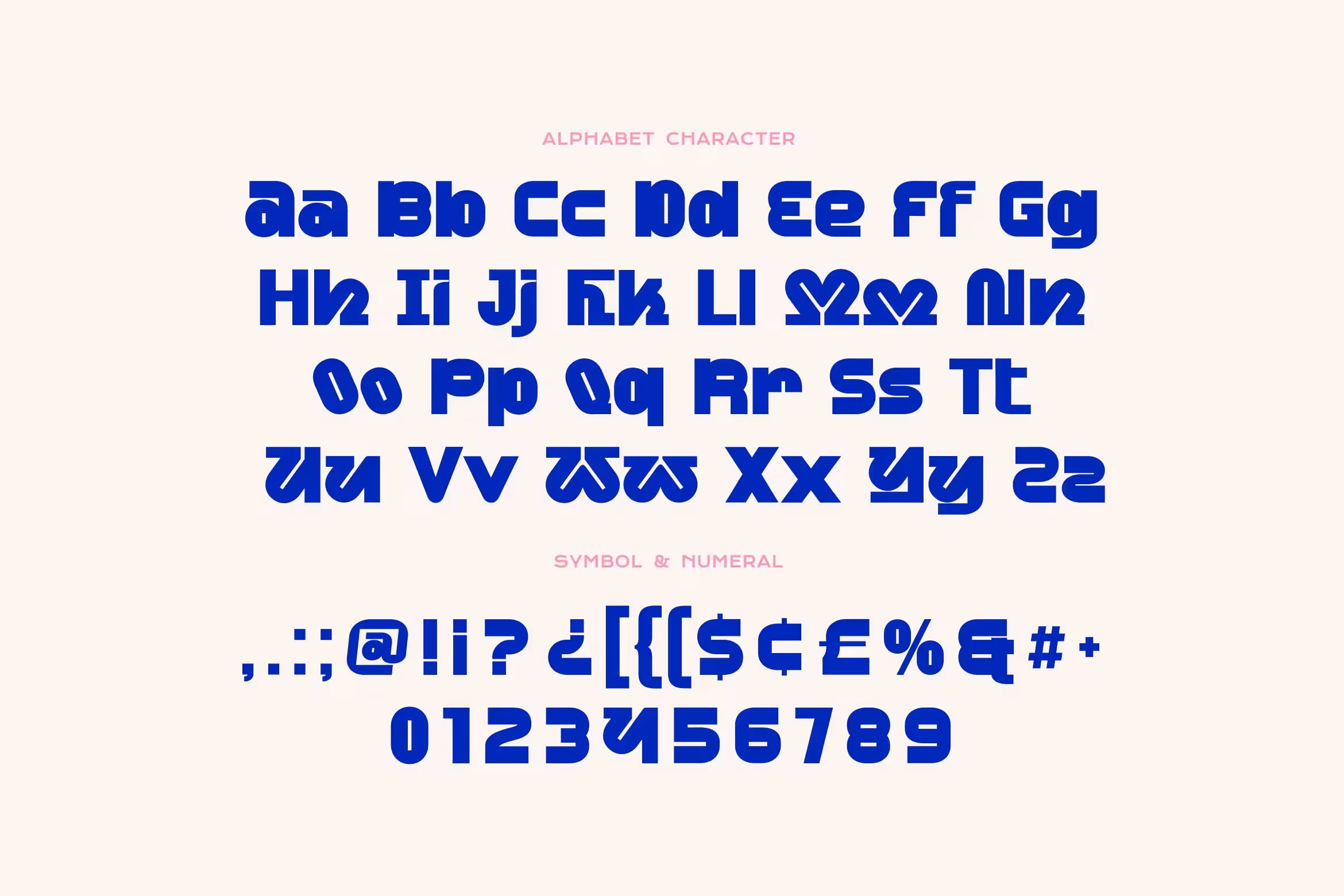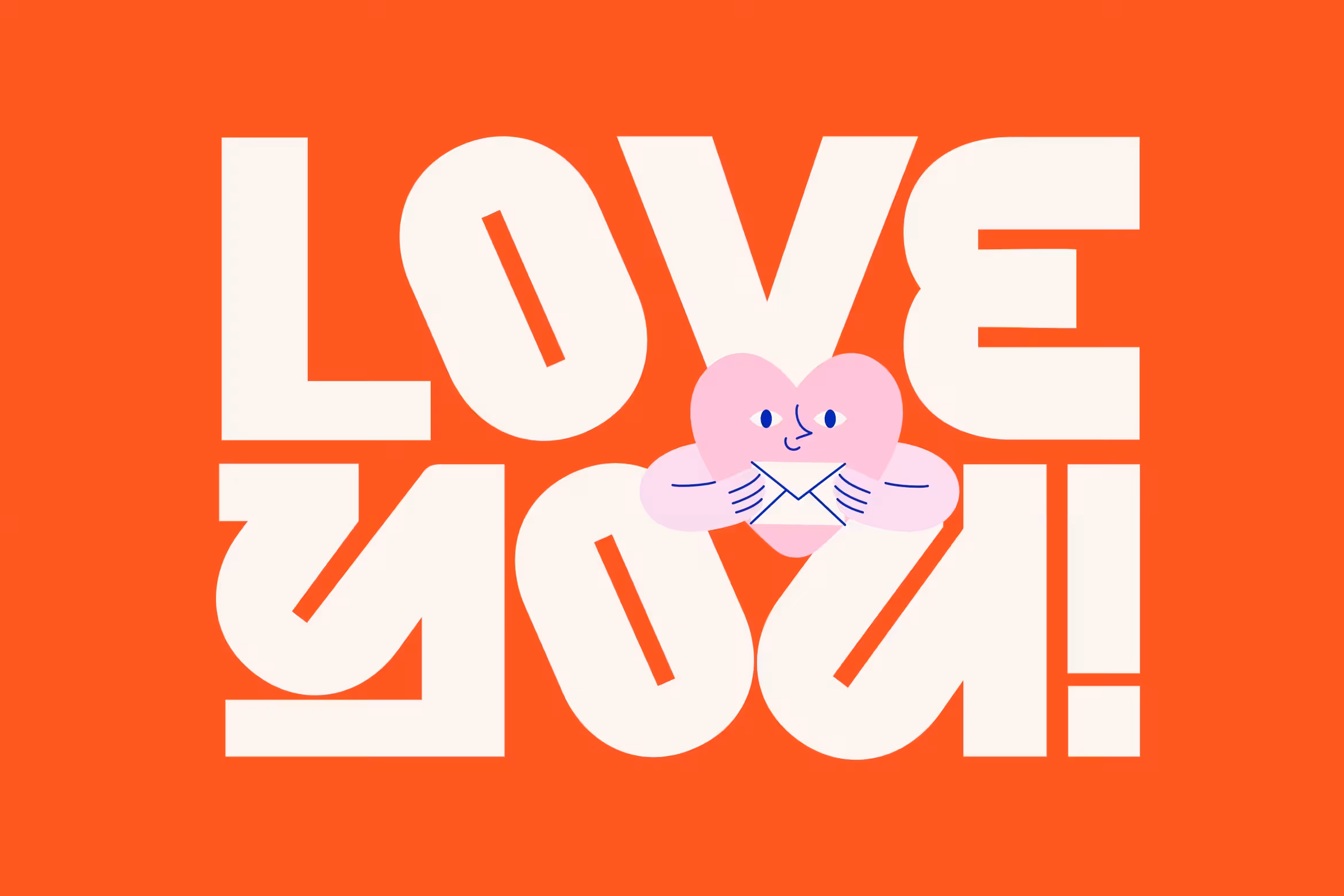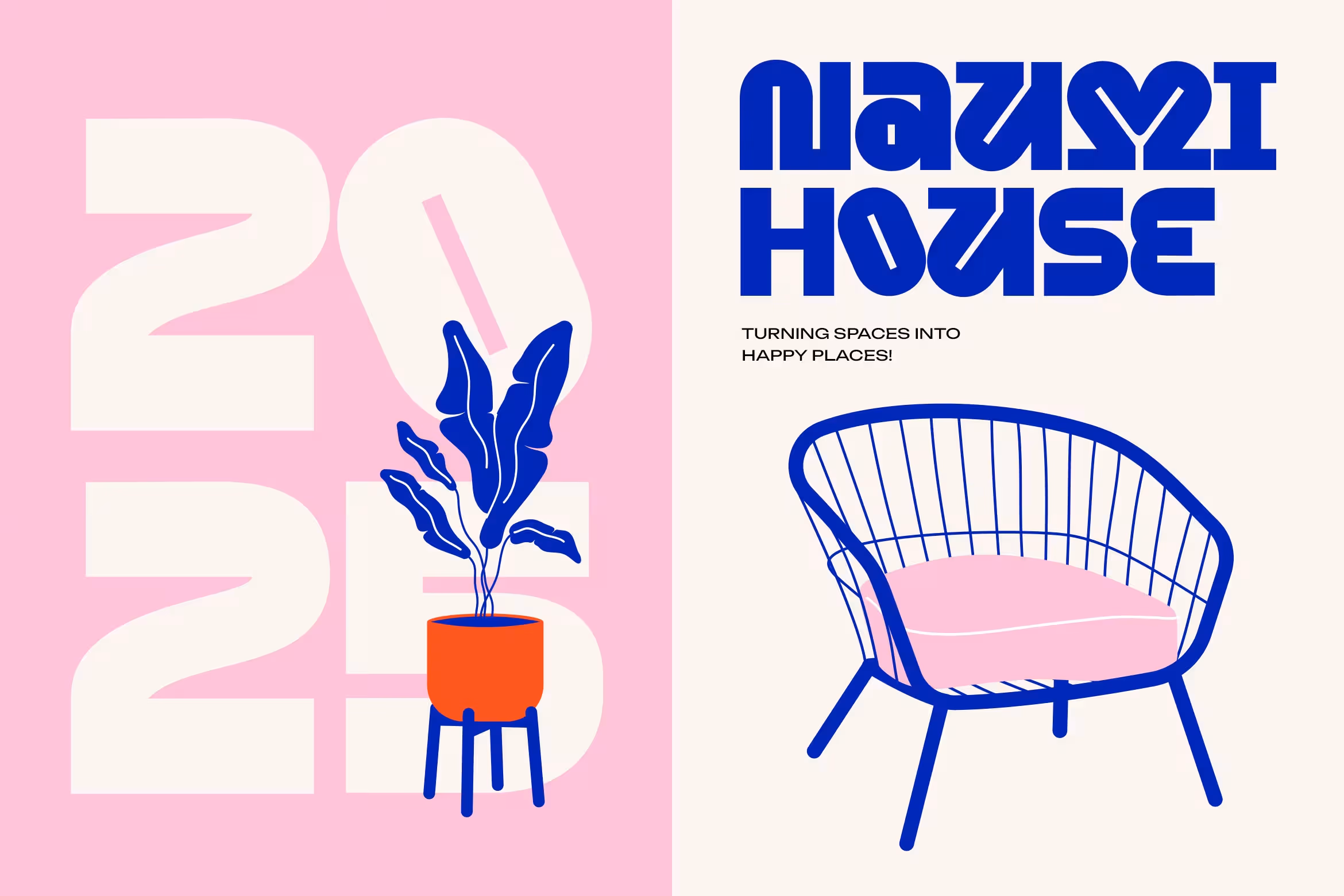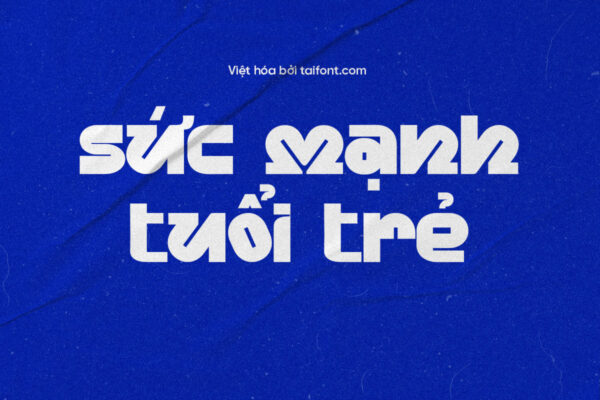
Giới thiệu về Font TF Owine Soul Việt hóa
TF Owine Soul Việt hóa là một font chữ không chân (sans-serif) nổi bật với vẻ đẹp mạnh mẽ, độc đáo và đầy thú vị, lý tưởng để tạo nên sự ấn tượng và cá tính cho các thiết kế. Font này toát lên phong thái hiện đại, vững chãi với những đường nét được chăm chút tỉ mỉ, đôi khi có những chi tiết phá cách nhẹ nhàng, tạo sự cuốn hút riêng biệt.
Với sự mạnh mẽ và tính thẩm mỹ cao cùng những nét độc đáo, Owine Soul là lựa chọn lý tưởng cho các ấn phẩm cần sự nổi bật và cá tính, đặc biệt là trong các lĩnh vực:
- Tiêu đề: Hoàn hảo để tạo các tiêu đề chính trên poster, banner, hoặc các ấn phẩm truyền thông cần sự chú ý tối đa. Nét mạnh mẽ và hình dáng độc đáo của Owine Soul giúp thông điệp của bạn “nhảy” ra khỏi trang, dễ dàng gây ấn tượng sâu sắc.
- Poster: Lý tưởng cho poster quảng cáo, sự kiện, hoặc các chiến dịch truyền thông cần thông điệp rõ ràng, mạnh mẽ và có phong cách riêng. Owine Soul sẽ giúp poster của bạn trở nên sinh động và đáng nhớ.
- Nội thất: Phù hợp để sử dụng trên các biển hiệu, bảng chỉ dẫn, hoặc các yếu tố trang trí trong không gian nội thất hiện đại, mang lại vẻ đẹp mạnh mẽ, cá tính và độc đáo cho không gian.
- Thiết kế thương hiệu: Có thể dùng cho logo, tagline hoặc bộ nhận diện thương hiệu muốn truyền tải sự mạnh mẽ, hiện đại, và một chút “chất” riêng biệt.
Với TF Owine Soul Việt hóa, bạn có thể dễ dàng thổi hồn mạnh mẽ, năng lượng và sự độc đáo vào các thiết kế, tạo ra những sản phẩm không chỉ đẹp mắt mà còn cực kỳ ấn tượng và có khả năng thu hút sự chú ý tối đa.
Font Việt hóa TF Owine Soul